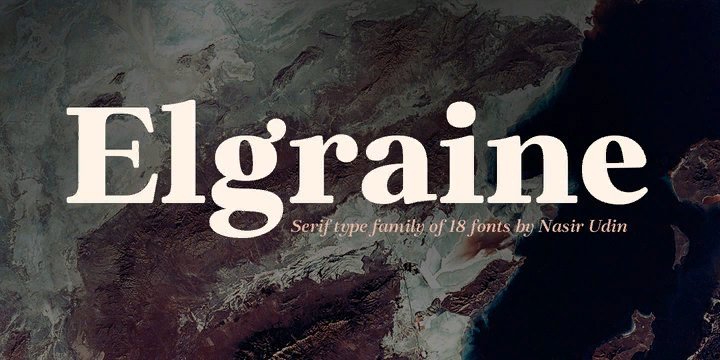
[Myfonts] Elgraine Font (2021)
Elgraine
- это шрифт с засечками, вдохновленный красотой классических засечек и каллиграфического стиля, соединенных с современностью.
Варьируясь от тонкого до черного с соответствующим курсивом, Elgraine предлагает множество возможностей для применения во многих графических и редакционных проектах. Легкий и обычный шрифт подходит для длинных абзацев, а более тяжелый - для ярких заголовков, идеально подходящих для таких целей, как брендинг, редакция и упаковка.
Elgraine имеет расширенный латинский набор символов, поддерживающий 200+ языков на основе латинского алфавита.